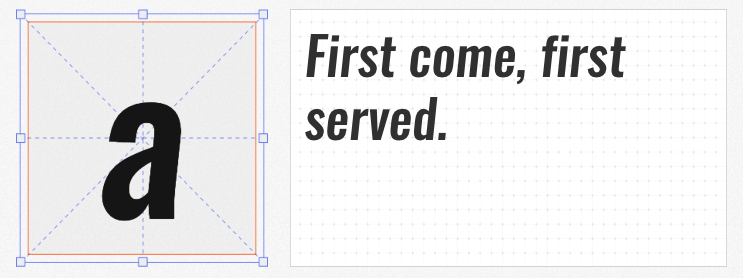
在视觉设计中,斜体英文字体常用于强调标题、品牌标语或营造动态感,而选择免费可商用的字体既能保证设计合规性,又能节省成本。本文推荐四款来自开源平台的斜体英文字体,它们风格各异,却均以高易读性和独特设计脱颖而出,适合从品牌视觉到数字内容的多元场景。
Rubik Italic源自专业团队设计的开源无衬线字体家族,通过Google Fonts免费开放。其斜体版本延续了正体的几何感,笔画简洁利落,却通过微妙的倾斜角度赋予文字动感。字体提供从细体到粗体的多重权重,无论是标题的轻盈感还是正文的层次感,都能轻松驾驭。尤其适合科技、时尚类设计,其现代感与屏幕显示的清晰度使其成为数字界面的热门选择。
Oswald MediumItalic是对经典“交替哥特式”字体的数字化重构,专为屏幕显示优化。设计师重新绘制了笔画细节,使其在低分辨率设备上仍能保持锐利边缘。斜体版本保留了无衬线字体的简洁,却通过倾斜角度增添了一丝复古韵味。适用于需要兼顾历史感与现代感的场景,如文化类网站、品牌标语或海报标题。
Montserrat Italic的设计灵感源自蒙特塞拉特岛的建筑线条,其斜体版本以干净的几何笔画和微妙的倾斜角度,传递出一种冷静而时尚的气质。字体结构紧凑,字母间距经过精心调整,即使在小尺寸下也保持高易读性。适合用于品牌标识、社交媒体视觉或包装设计,尤其能凸显年轻、活力的品牌形象。
作为一款衬线字体,Lora Italic的斜体版本融合了书法笔触的流畅感与现代印刷体的规整性。设计师通过调整笔画粗细对比和倾斜角度,赋予文字一种优雅的叙事感。适用于长文本排版、艺术类文章或品牌故事展示,其独特的“印刷声音”能瞬间提升内容的文化质感。